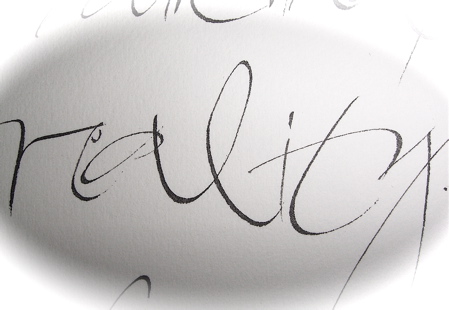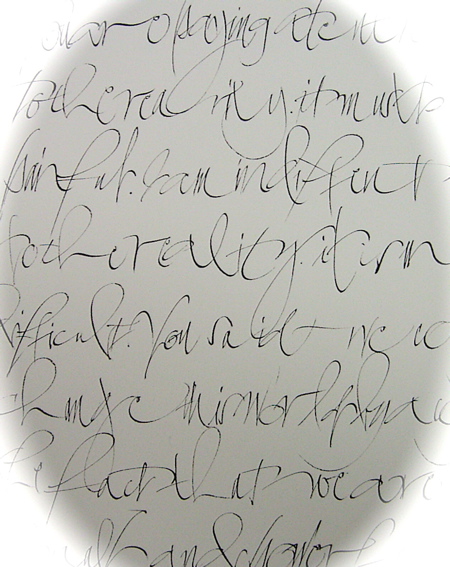
鉛筆でカリグラフィー
これらは先日代々木で行なったクラスの、生徒さんたちの出来上がり作品です。
すべて鉛筆で書いたイニシャルです。
文字の様にも見えるけど、模様でもあり、どれも本当に良く書けてるでしょう!美しいですね。
文字同士が入り組んで、とても立体的に見えて来るので、不思議。
鉛筆の塗り方でもずいぶん違って見えますね。
薄くても濃くても、それぞれがとても美しい。
さて、こちらは塗ったり消したりしながら、文字を重ねます。
所々陽が当たっているような、格子の陰になっている様な・・・・。不思議な効果です。
同じ言葉ではなく、違うことばが重なっているのもありますよ。
本当はもっともっとたくさんの画像を撮りましたが、すべてをご紹介出来ずに残念です。ここから発展させてどんどん面白い作品に応用していけると良いですよね。
期待しています!
鉛筆でいこう
代々木でのクラスでしたが、今回は鉛筆で楽しむという内容でした。いつもインクやペンや絵の具で書いていますが、たまには乾きものもいいものです。
ダブルペンシルやカーペンターペンシルで文字を書くのは、なかなか気持ちがよいですよ。ペンとは違って摩擦がないから、スルスルっと手が動きます。
コツは下敷きにたくさん紙を置いてクッションをつくること。そうすると、鉛筆が適度に沈み、線がちゃんと出てくれます。けしごむの使い方もポイントですね!書いて消し消し、そして書く。
ひとつひとつの文字が大きくなるので、手を一杯動かさないとなりませんが、やわらかな感触なので書きやすいです。
←こちらは、鉛筆で書いた上にペンと顔料系のインクで書きました。
くっきりした黒なので、文字が映えますね。
このクラスは、2時間の中で練習をやってそれから小作品づくりなので、いつも大忙しですが、みなさんの手際の良さとコツの掴み方が上手なのとで、いやいや、いつも感心しきりです。
みんなの作品はまた後日ご紹介しますね。
あ、そう言えば、最後に作った作品は撮影し忘れました!!とっても完成度が高かったので、あ〜、残念!
鉛筆やチャコールを使いこなせたら、世界が広がりますね。
もっと追求してみましょうか!
1.アンジェリーナ 君が忘れた靴 2.バルセロナの夜 光が導く物語 3.彼女はデリケート ベジタリアンの口紅 4.誰かが君のドアを叩いている 首にかけた指輪 5.奇妙な日々 一番思い出したこと 6.ナポレオンフィッシュと泳ぐ日 水のないプール 7.また明日 金のピアス
8.クリスマスタイム・イン・ブルー 聖なる夜に口笛吹いて 9.ガラスのジェネレーション プリティ・フラミンゴ 10.情けない週末 コンサートが終わって
佐野元春さんの歌詞の後に小川さんの小説が続く…。歌は、少しリアリティを含むと…個人的に受け止めるが、小川さんの小説では、日常の歪みみたいなものに遭遇する。とても危うかったり、とても恐ろしかったり…そしてあまりに美しかったり…。それでもどこかに救いがあって、何かに気付かされる…。「誰かが君のドアを叩いている」で、主人公の女性は、最初に左足の記憶を失う。女性は
不思議な温室で身体の記憶を失いながら、そこで出会った男性のもとですの姿を受け入れていく…。小川さんの小説では身体の一つ一つが消えていくお話しが他にもある。そんな奇妙な…と
思う反面、見える物の記憶はあいまいなのかもしれないと思い直す…。BUMP OF CHICKENの Supernovaでも熱が出たりすると自分の身体に気付くということを歌っている…。
何だか得体の知れない素敵さだ…。
貴婦人Aの蘇生 (朝日文庫)
ロマノフ王朝の話しが絡んで不思議さを紡いでいく…。
こちらも、現実なのかそうでないのか…何が本当で、別に
本当でなくてもいいのか…。
不思議な世界…。
どうしてこんなにも淡々と長編で書いていけるのだろう…。
自分の住んでいる世界とは別の時系列で存在している人達が
それでも、本当は自分も同じ時間に生きているのかもしれない…
と心地良い思いを自分の中に蓄積できる…。
身体は疲れていたけど、小川さんの本を読んで心がゆっくりできた…。
そんな週末でした…。
2008年05月07日
ガムサンダラック入れ
おや、めずらしい、縫い物ですか?
はい、ガムサンダラックを入れたバッグがきたなくなっていたので
新しくしました。
布地を丸く裁って(別に四角でも構わないのですが、見た目がきれいだから)適当なサイズに縫います。やや太めの糸(刺繍糸くらい)を使いました。布の色は何でもよいと思うのですが、やっぱり白が気分、です。
中央にサンダラックを置きます。
糸をしぼってグルグル巻きにします。てるてる坊主のさかさま版です。
書いている紙の上にポンポンとすれば、適量の粉が簡単に出ま〜す。便利ですね。粉を買ったときの入れものや
小さな空き瓶、フィルムケースなどに、このバッグのまま入れておきましょう。
布地の目がやや粗かったので、布を二枚重ねにしました。
ほんの2〜3分でできますよん。面倒なら輪ゴムで巻いてもOKです。
2008年05月06日
あんなもの、こんなもの…。
え〜っと…、ガーラには日帰りでしたが、他は頼まれ仕事が
進まず…。はぁ…sさんみたいに自分の時間を有効に使え
ませんで…。(汗)
…なもんで、これといって話題もなく、
…で、
1月にお話ししたSt.Antonでカシャ
!こちらでは見ないあんなもの
こんなもの…で、ブログネタ潰しか?
上をご覧ください!あんなに急斜面を降りてきて…なのに向こうへ行くにはロープにつかまり運ばれねばならぬのです…。ちょっとマヌケ?って感じ(笑)。
…何の変哲もない案内板…。
って、絵を良く見れば…何かリフトがワサワサ!?
「1…2…3…??」人数やけに多いぞ!?
そうです。8人乗りリフトが待ち受けてる!
ちなみにこのスキー場(Lech)はお金持ちが滞在するので、
ヒーター入りでお尻がヌクヌクリフトもあるんだよ!
ほらね!これは故ダイアナさんがスキーで滞在していたと
いうホテル!
北欧の王室が宿泊するホテルも向かい側にあるし〜!
もちろん、絶対に私達は泊まりません…って泊まれせん…って!
破産しますから…。本当だよ〜!St.Antonから車で30分走れば
滑りには来られるんですぞ。
左の青い看板があったら…ちょっと注意!?動く歩道状態ですから…。
スキー板はいたまま自動でリフトの位置まで運んでくれてそのまま乗ります。ちょっと変な気分!
オーストリアの郵便は黄色が基本!ポストも黄色ですから!
赤より目立つかも…。
St.Antonの子供プログラムは充実!スキー学校の先生がこんな可愛い乗り物で迎えに来てくれますよ!!
以前ご紹介しましたが、宿の
情況はこれで判断!どの宿も
部屋の空き情報を外からわかる
ようにしていますよ!
赤いと満室です!緑だと空いてる意味です!
どこの町でもだいたい一軒は中国料理のお店…ありますねぇ〜。
すごいなぁ…。
でもついついお世話になっちゃう…。
こういう看板が必ずどこのレストランでも道に出てますね!必ず手書き!
…皆様はどんな連休をお過ごしだったのでしょうか…。
今日、ブログを見てくださった方…「げっ〜、こんなネタか…」と呆れてしまわれるかも…。
お粗末さまでした。世の中いろいろです。
2008年05月05日
失敗
・・てな具合に大きな紙に書いてみます。
動かしすぎず、やりすぎない様に、でもlivelyに。淡々と、シンプルに、でも何かを訴えてくれる様に。
ひとつひとつのストロークすべてが美しくというのは、本当に難しいもので、何枚書いても、なかなか思った様には全然、そう、ぜ〜んぜん書けません。
ん!なかなか良い具合で書けてるぞ、と思った瞬間、ありゃりゃ、と失敗ストローク。
今回は自分のことばを書いています。あのブロディ・ノイエンシュヴァンダー氏がギャラリ―トークで言っていた様に、日本ではその昔、詩人(歌を詠む人)は自分でサラサラと達筆で文字を書いていた訳で、それにならって書いてみた訳です。その方が、読む人にはうまく伝わるのかもしれません。(だからと言って自己満足にならないようにしないとね・・・)
でも、もうこのあたりが限界。どんどかけて行きますので、徐々にしっかりかかってしまう部分が増えて行き、そうなると、最後ははじきすぎて文字がのらなくなります。
いろいろと試してみていますが、結論から言うと、いろいろ組み合わせがよさそうです。
まずガッシュにアクリル系のメディウムを入れて耐水性の絵の具にして書く。または、アクリル絵の具で書く。
その上にかる〜くささっとフィクサをかける。(アクリル系の絵の具の上は、細い線がやはり出にくいですからね)次はガッシュで文字を書く。
書いたらもう一回フィクサ。その上に今度もガッシュで文字を書いたら、今度はサンダラック。そして、またガッシュで文字を書いて、もう一度サンダラック。
たぶんこのあたりで、もう限界になると思います。はじいてしまうでしょう。
レイヤーの作品は、奥行きが作れるし面白い効果が出るのでやりたいですが、どこまでも美しい線を出すのは難しいです。
他にも方法はあるかも。
あ、そうそう水乾絵の具は、重ねても大丈夫でしたっけ!!文字を何度重ねてもきれいに書けたような気がします。ってことは、にかわがいいのかな?
試してみる価値ありそうですね。やってみませう